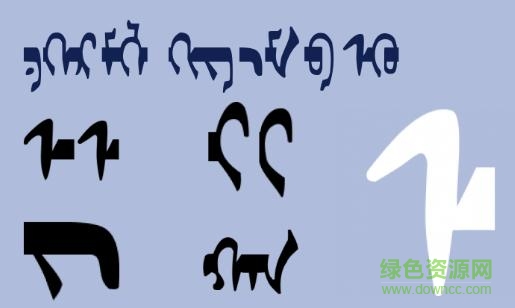
mwbit字體是一款設(shè)計(jì)效果不錯(cuò)的蒙文字體,筆畫單純,結(jié)構(gòu)嚴(yán)謹(jǐn),風(fēng)格穩(wěn)重,可廣泛應(yīng)用與蒙文相關(guān)的廣告、影視、網(wǎng)站等方面,需要的小伙伴快來免費(fèi)下載吧!
早期的蒙古文字母讀音、拼寫規(guī)則、行款都跟回鶻文相似,稱作回鶻式蒙古文。